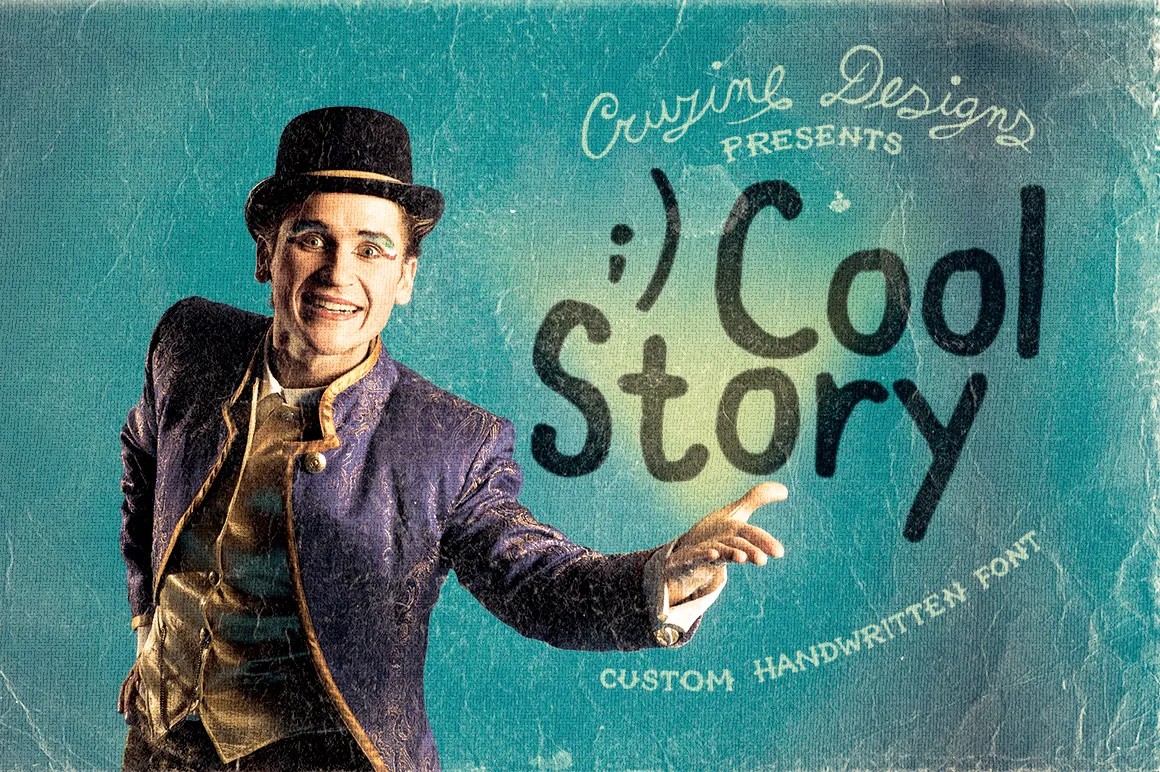
Cool Story Font – Download Grátis
A Cool Story Font é uma elegante escolha para quem busca uma mão-direita delicada e deslumbrante, perfeita tanto para títulos quanto para texto de corpo na sua próxima criação visual. Desenvolvida pela Cruzine Design e cuidadosamente criada pelo designer Hamilton, essa fonte não só traz um toque autêntico à sua obra, como também uma sensação fresca e contemporânea que certamente fará a diferença em seus projetos. Com traços leves e fluidos, a Cool Story Font captura o espírito descontraído de um caderno pessoal recém-aberto. Seu estilo delicado é perfeito para ilustrar histórias singelas ou desenvolver um tom emotivo nos textos mais complexos. Para quem busca uma fonte que ofereça tanto beleza quanto versatilidade, a Cool Story Font é definitivamente o item de desejo. Descarregue-a e experimente o prazer de criar com esta mão-direita única e criativa. Você não encontrará um estilo igual em qualquer lugar.